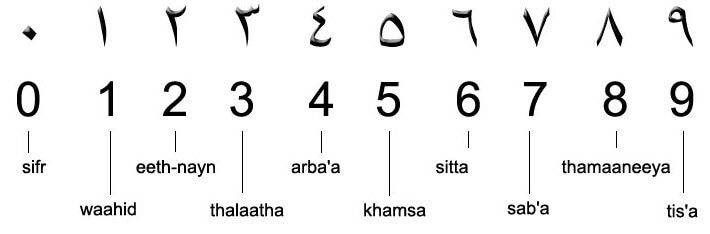
InDesign: Fragen zum Satz von Persisch und Arabisch …
Hat jemand schon mal in InDesign Persisch setzen dürfen? Die Grundzüge sind mir schon klar, InDesign (mit der arabischen Erweiterung) macht das auch prima, die Zeichen stimmen mit der Vorlage überein. Ligaturen sind ausgeschaltet.
Welche Sprache muss denn in ID für den persischen Text eingestellt werden? »Arabisch«? »Keine«? »Persisch« oder »Farsi« bietet ID ja nicht an …
Welche Zahlform wird denn im Persischen üblicherweise verwendet? Die europäische (unten) oder die arabische (oben) Darstellung?
Wohl eher keine der beiden, sondern die persische Variante der (ost)europäischen Zahlform, siehe z.B.
Ob die fehlende Spracheinstellung in ID ernsthafte Konsequenzen hat – oder ob es reicht, Fonts mit persischen Varianten zu benutzen, weiß ich nicht.